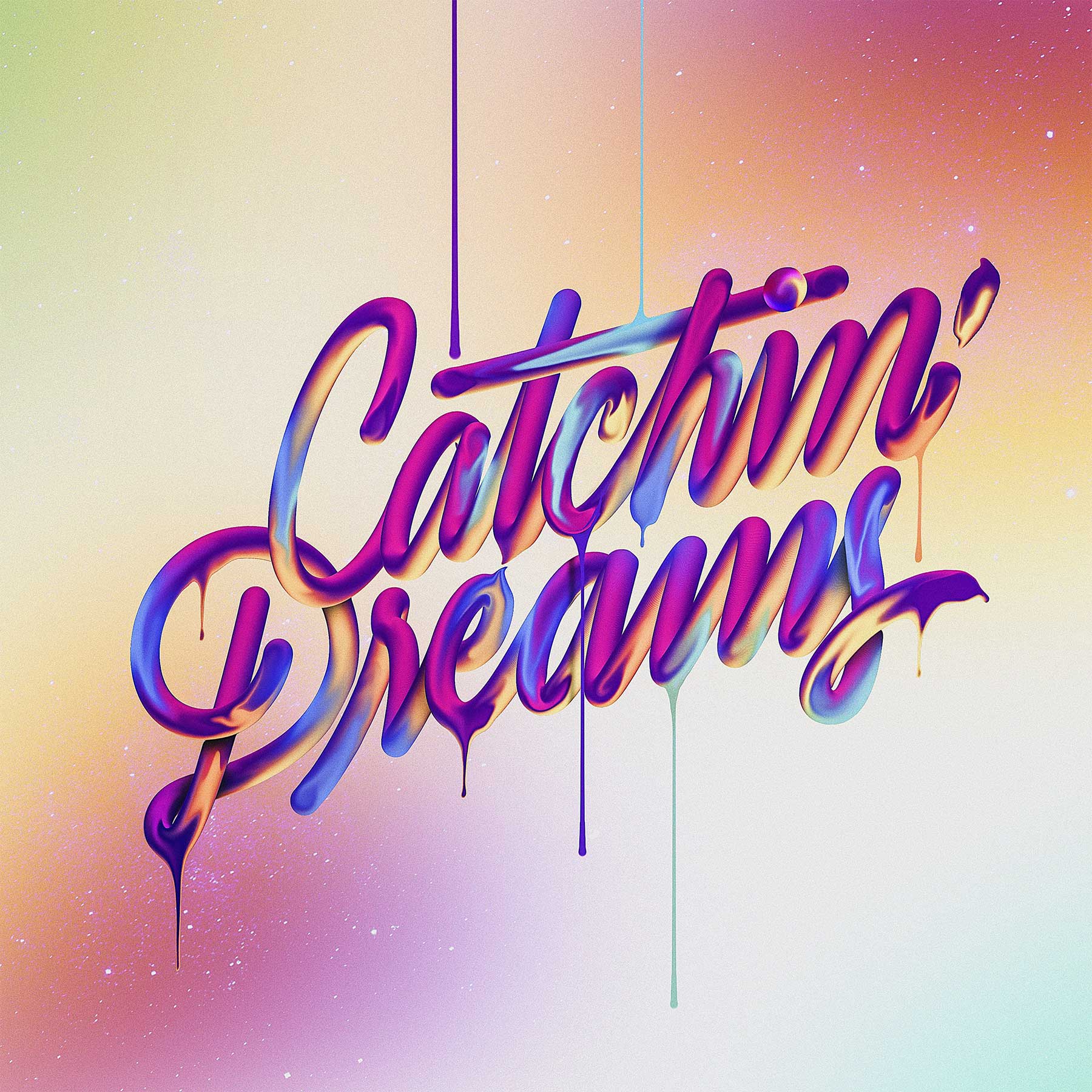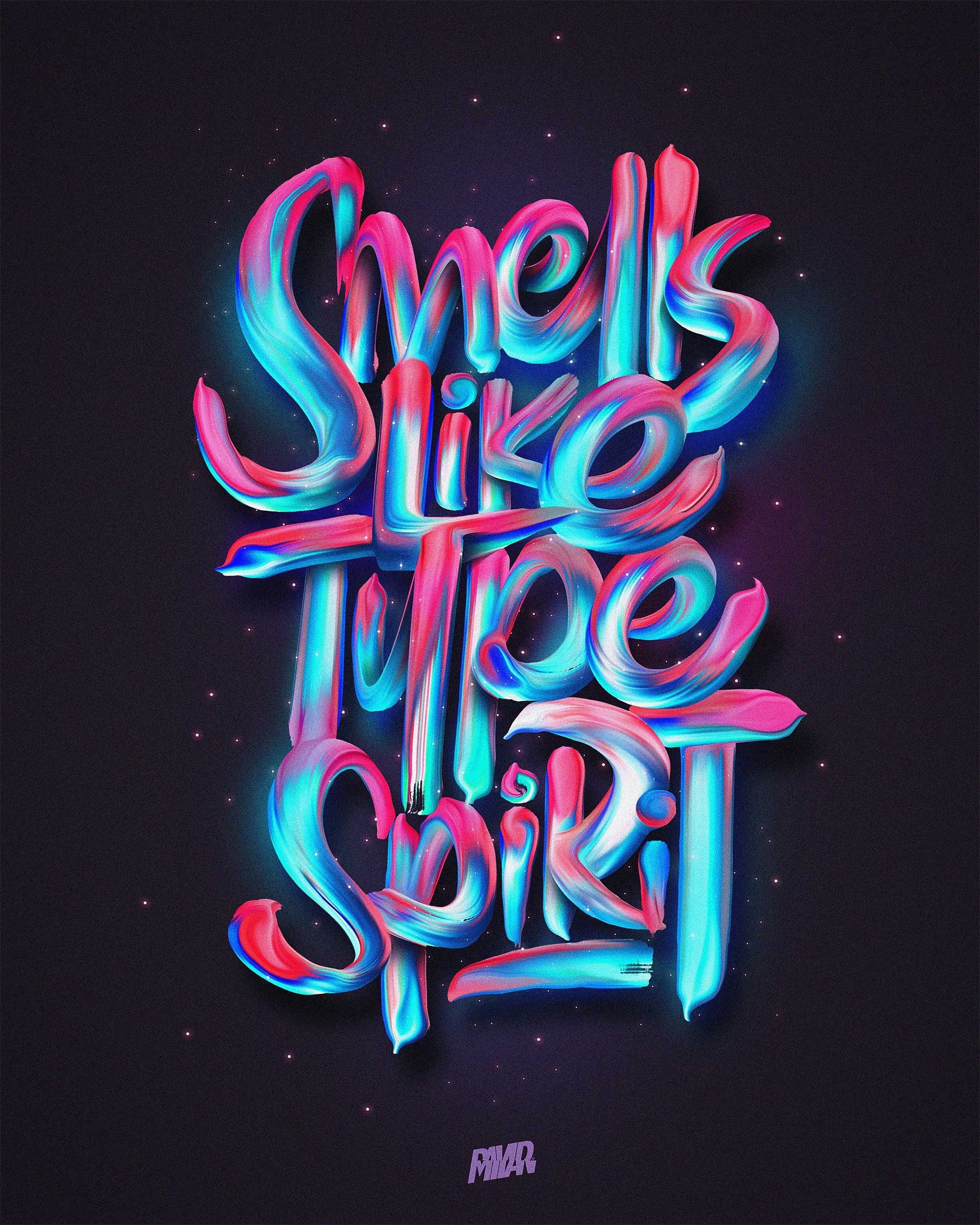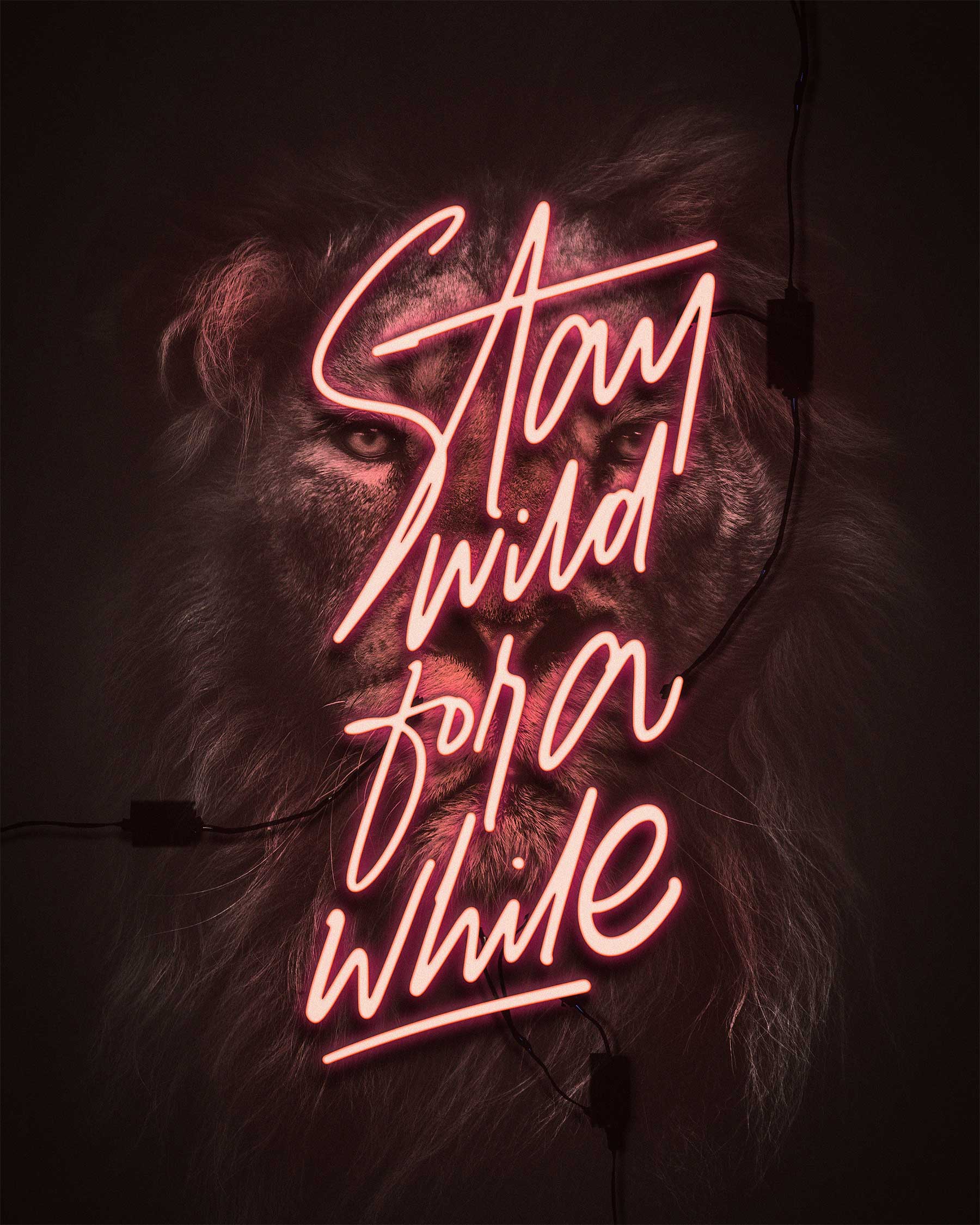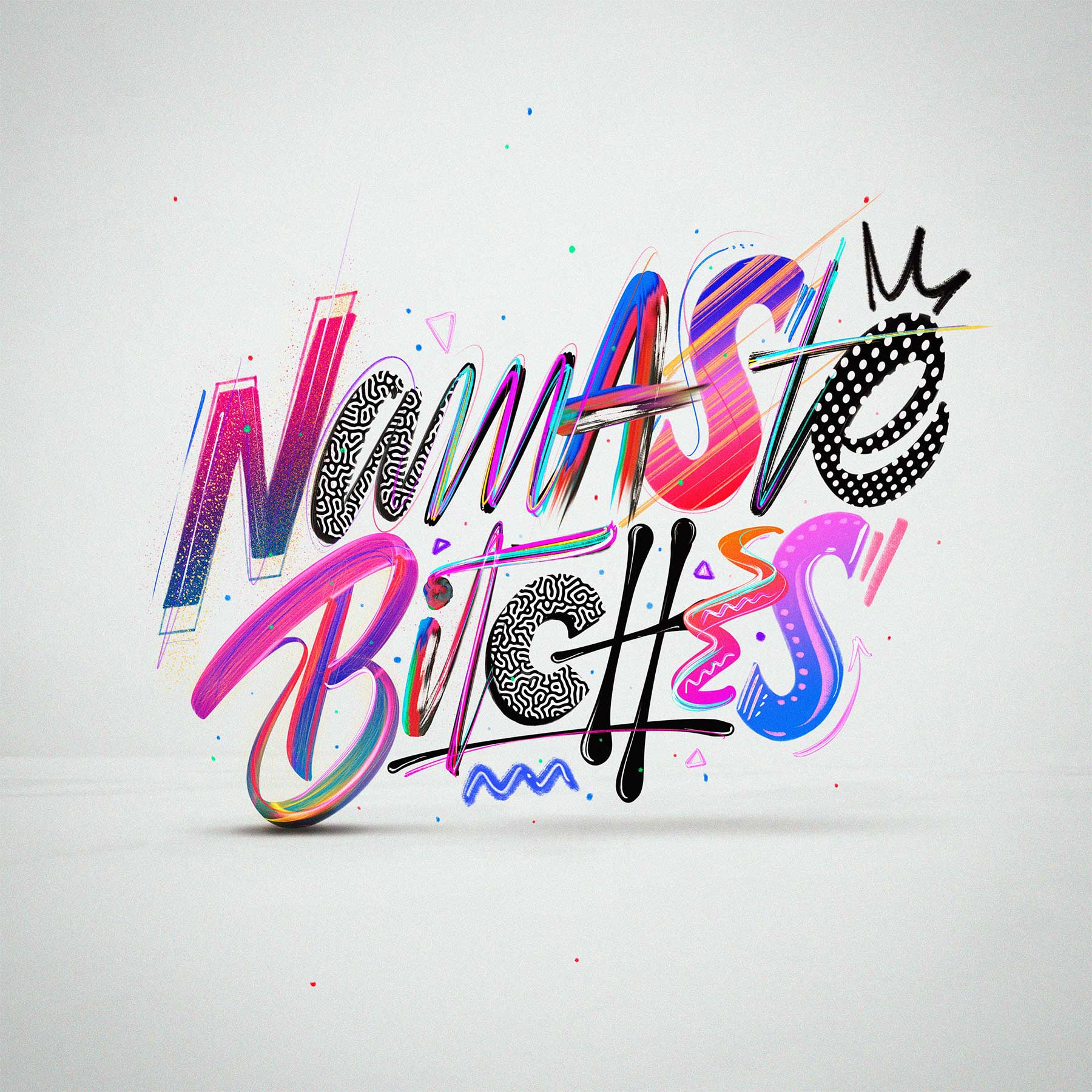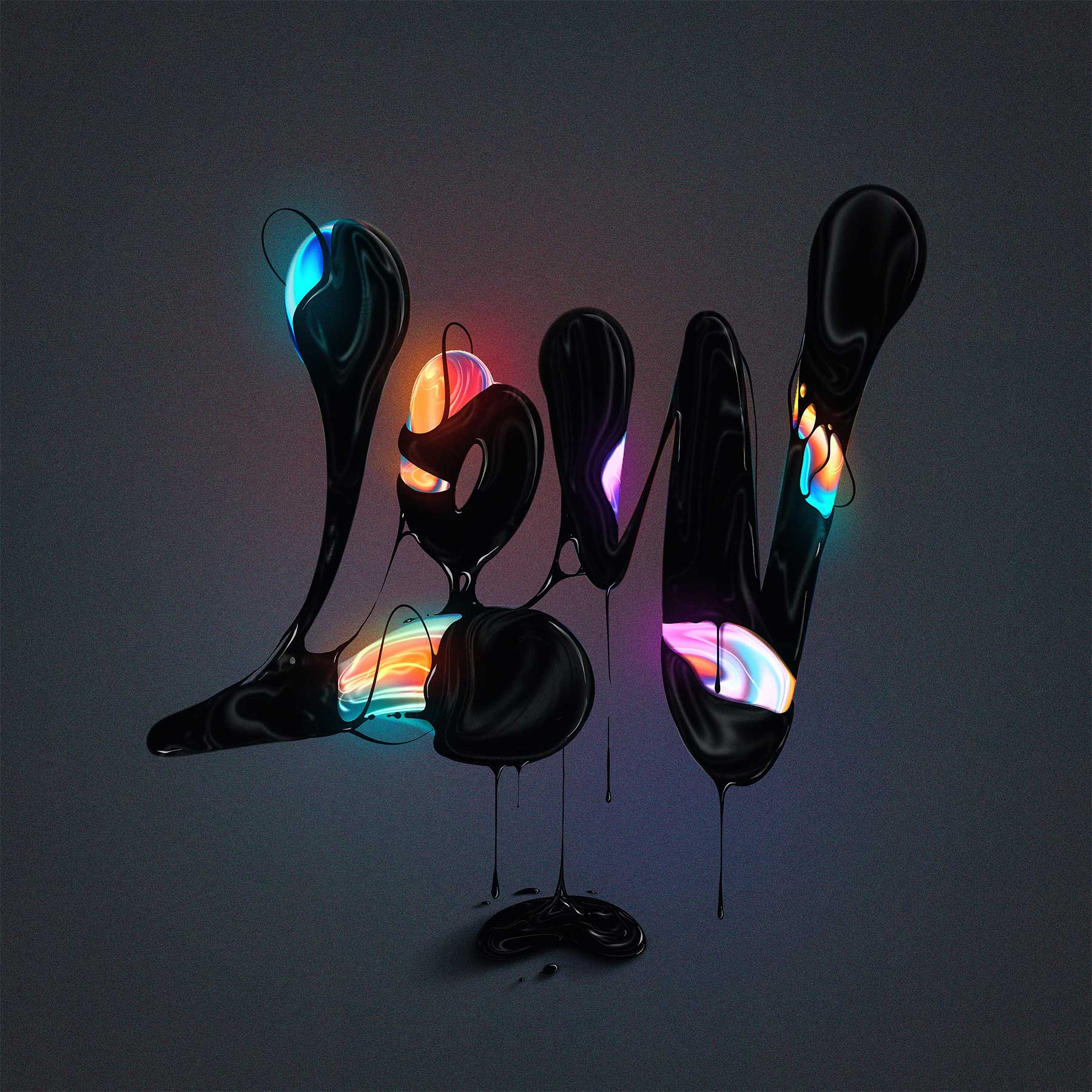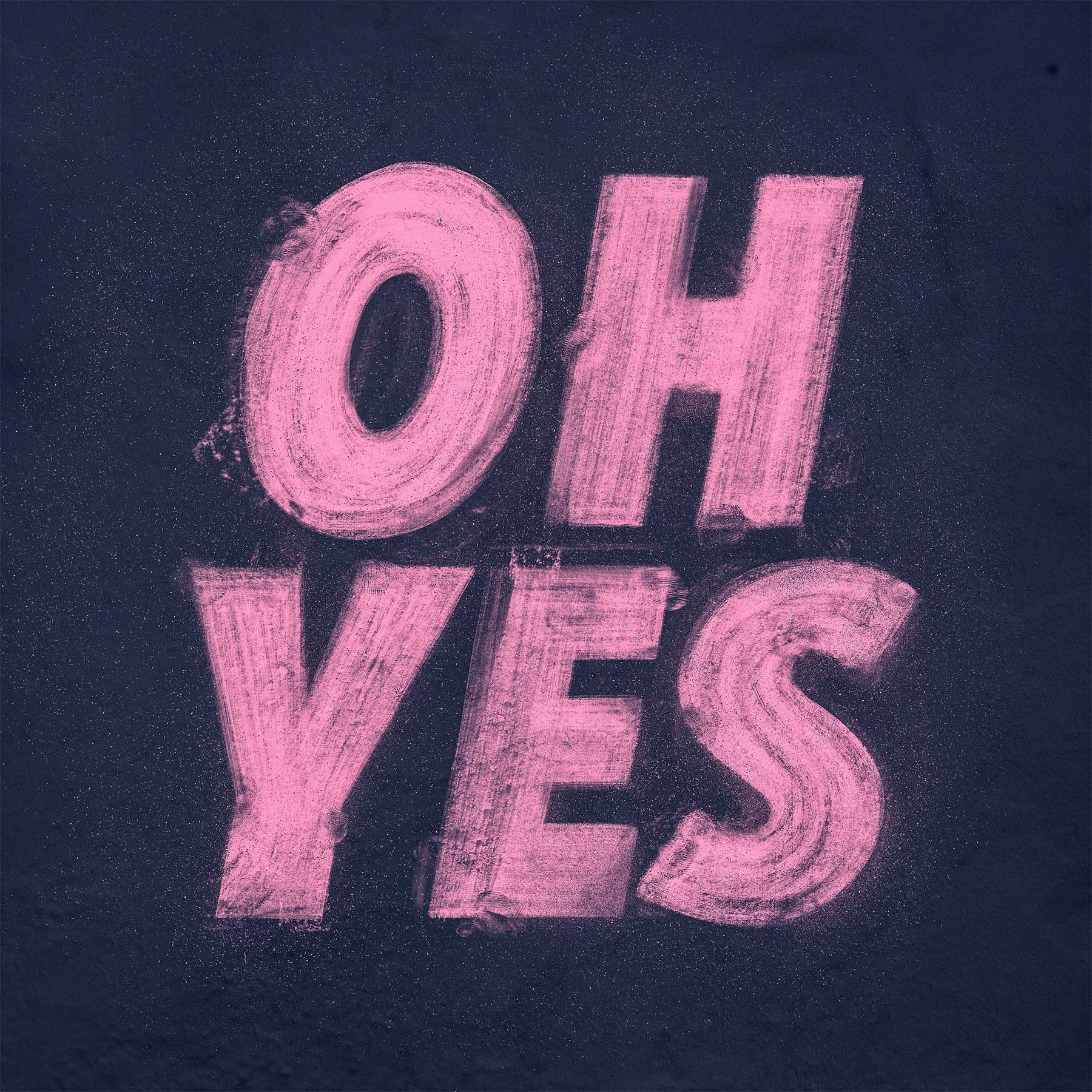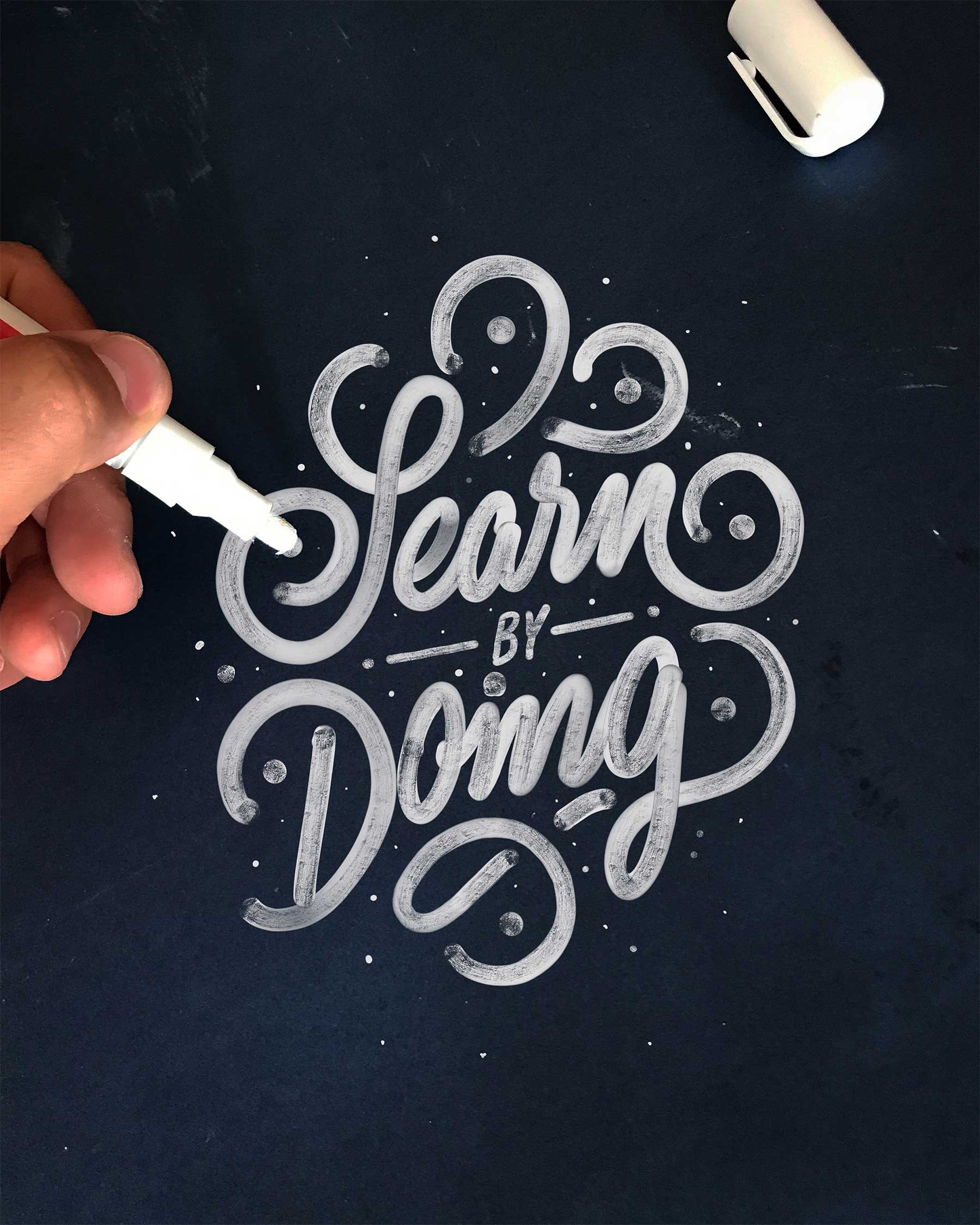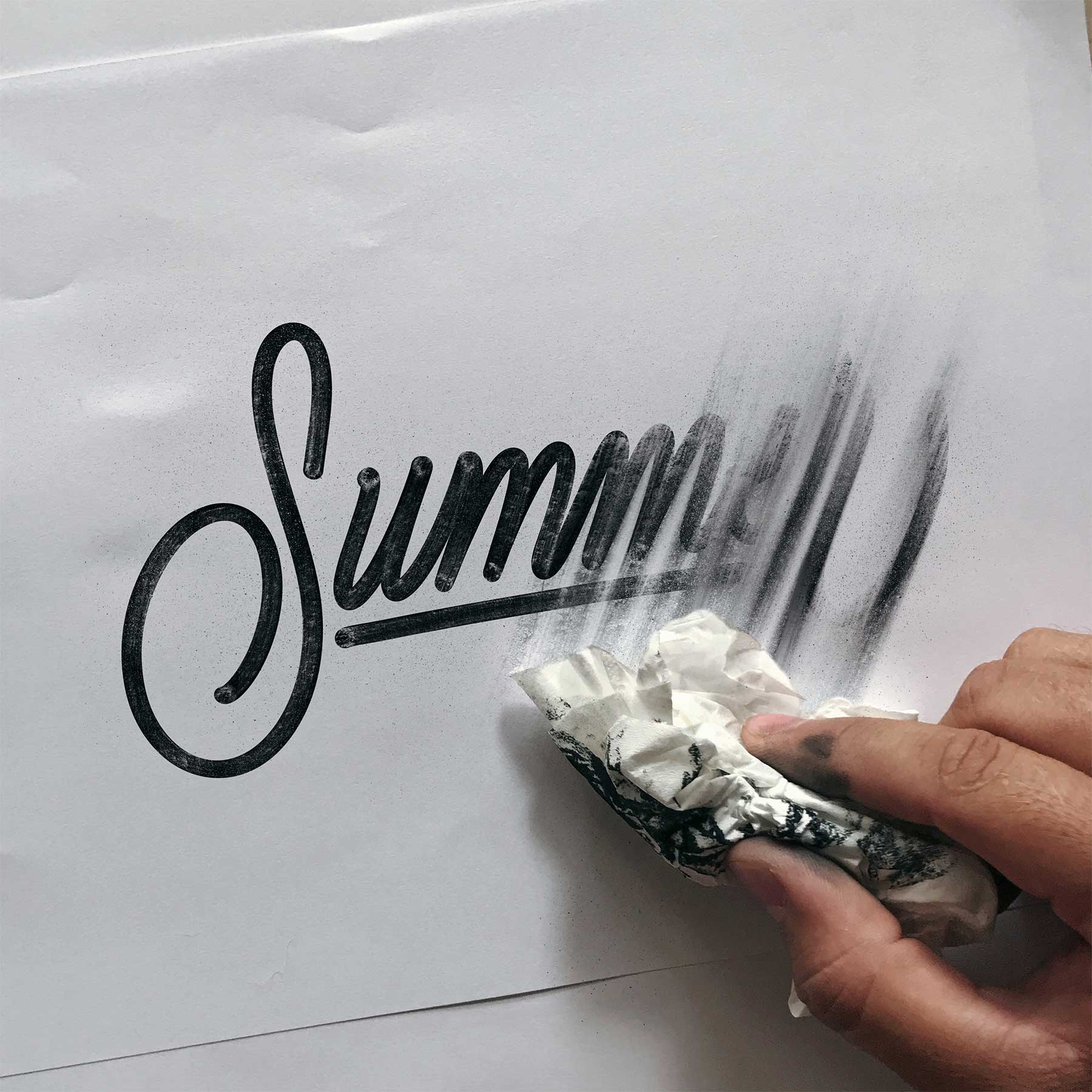
Experimentierfreudiger Buchstabensatz
Typografie: David Milan
Typografie: David Milan Typografie-David-Milan_01
David Milan kommt verwirrender Weise aus Madrid und spielt gerne mit Buchstaben und Darstellungstechniken herum. So sind seine Typografie-Motive erfreulich abwechslungsreich und werden daher nie langweilig. Da sind einige sehr schöne Ideen dabei, wie man die guten alten Buchstaben richtig schön aussehen lassen kann.
„First experiment collection I made using different techniques with my own calligraphy and lettering works. I like to explore, get inspired by other artists and see what comes out. As you can see I love to use colors, shapes, gradients, high contrast, paint and real textures.“